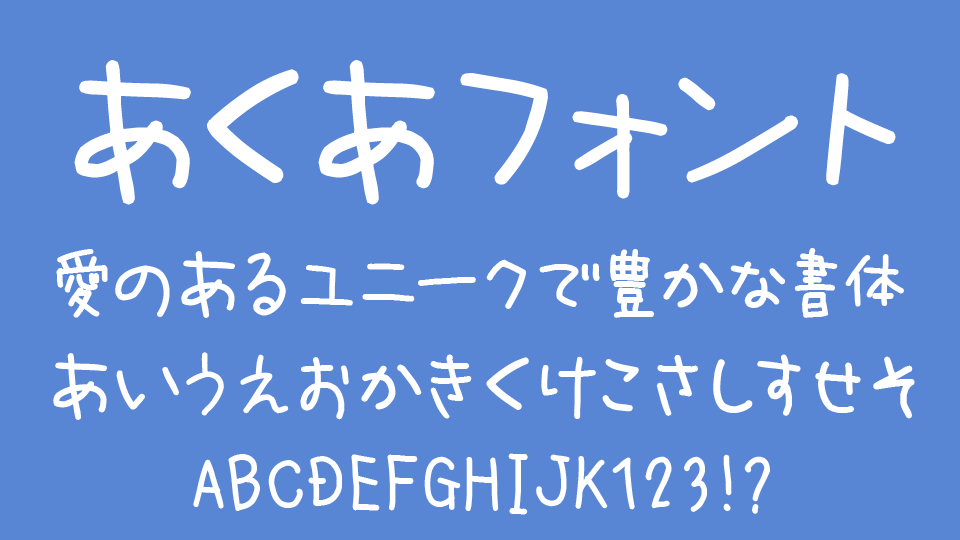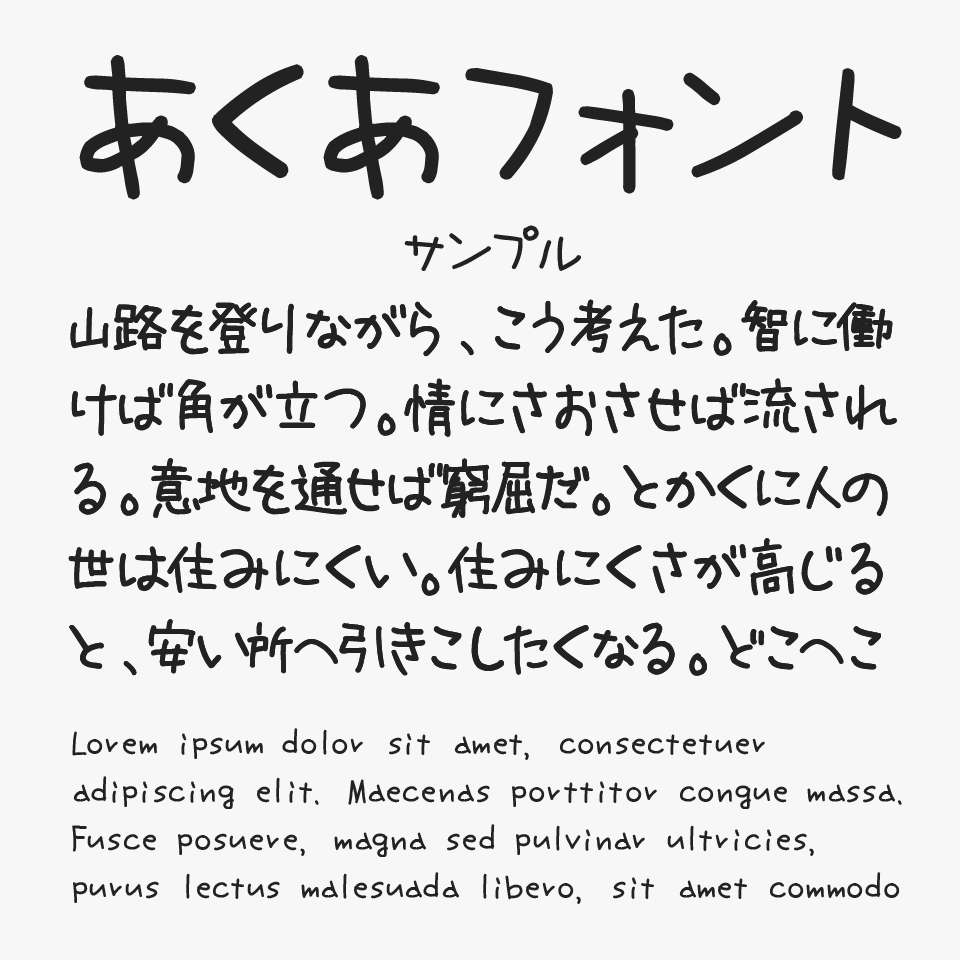
あくあフォント
あくあフォントは、手書きならではのやわらかな線が魅力のとっても可愛らしいフォントです。
文字全体に力の抜けた自然な揺らぎがあり、親しみやすさと爽やかさをあわせ持っています。角のない優しいフォルムは軽やかな印象を与え、見ているだけで涼しさや透明感を感じさせてくれる、ナチュラルな雰囲気のフォントです。
あくあフォント同盟というグループあったほど、人気があり、一世風靡した手書きフォントです。個人的にもとても好きです。
ナチュラルな手書きの雰囲気がとっても素敵ですよね。
あくあフォントを、ほかのやわらかくて手書きフォントと比較してみると、自然な丸みと軽やかな線によって、まるで日常の中でさらりと書いたような親しみやすさがある手書きフォントです。
比較フォントは、「梅干チュラル」「ちはや純」「れいこフォント」「えんぴつ楷書」「壱城ラウラ」「こよみゆるフォント」を使用していますが、どれも可愛らしい手書きフォントなので、ぜひあわせてチェックしてみてください。